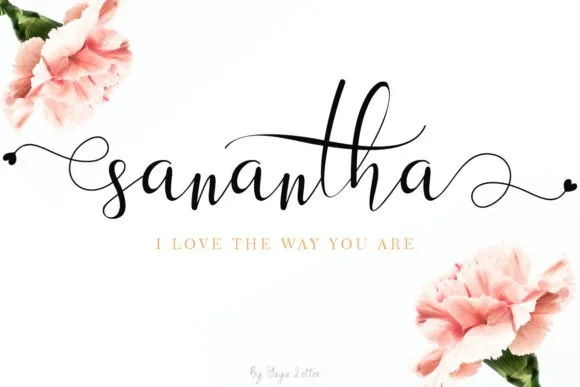
Sanantha Calligraphy Font
A Sanantha Calligraphy Font é uma elegante escolha para quem procura um estilo script fluido. Feita pelo designer YogaLetter6, essa fonte incorpora padrões estilísticos e alternativas estilizadas, tornando-a simplesmente perfeita para uso em projetos que valorizam a fluidez e delicadeza da escrita manual. Além disso, é PUA (Portable User Access) codificada, o que significa que você pode acessar facilmente todos os gílitos e swashes sem qualquer desafio. A Sanantha possui uma base de linha variável e linhas suaves, com gérmetis exuberantes e alternativas impressionantes. O resultado é um texto tanto clássico quanto atual e fresco, mantendo as influências das caligrafias tradicionais ao mesmo tempo em que se apresenta como uma fonte contemporânea. Adoraríamos ter a Sanantha na nossa próxima campanha de design – ela certamente elevará qualquer projeto!